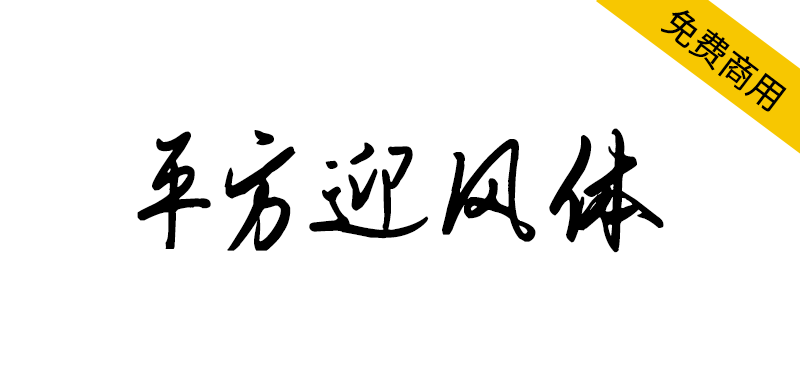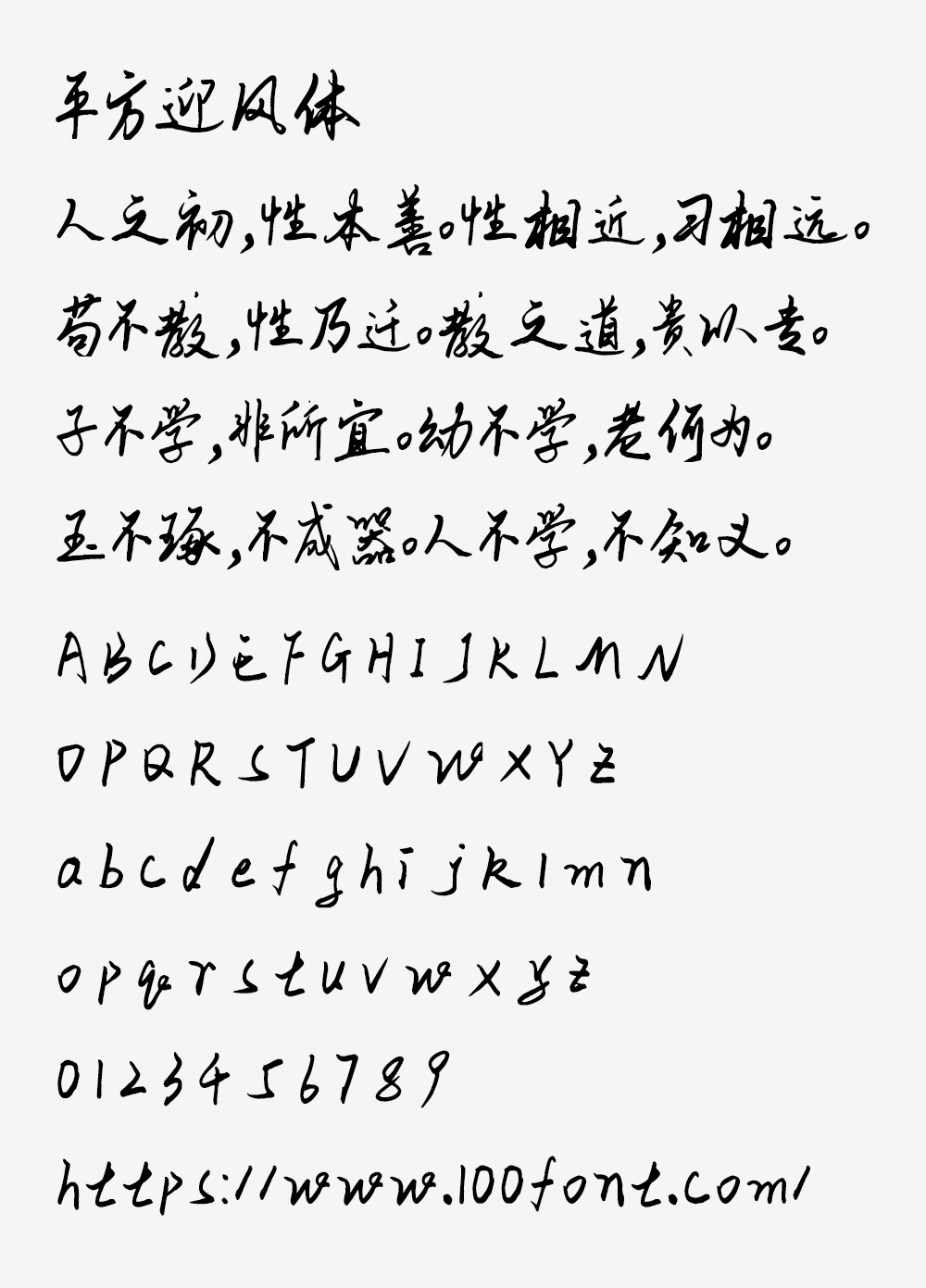
【平方迎风体】一款融合传统书法美学的艺术字体
还在为设计作品缺乏文化底蕴而烦恼?这款「平方迎风体」完美融合传统书法美学与数字设计,用流畅连笔重现毛笔书写的韵律感。最令人惊喜的是,它完全免费商用!无论是广告设计、自媒体排版还是电商页面,都能立即提升视觉质感。但要注意:虽然开放商业使用,却禁止修改字体或用于商标注册。想为你的创意作品注入东方美学灵魂?现在就来获取这款兼具艺术性与实用性的字体吧!
【平方迎风体】一款融合传统书法美学的艺术字体
平方迎风体是一款融合传统书法美学的艺术字体,保留了毛笔书法的核心特征,其独特的连笔设计赋予字体流畅自然的韵律,整体呈现洒脱飘逸的视觉效果。
【平方迎风体】一款融合传统书法美学的艺术字体